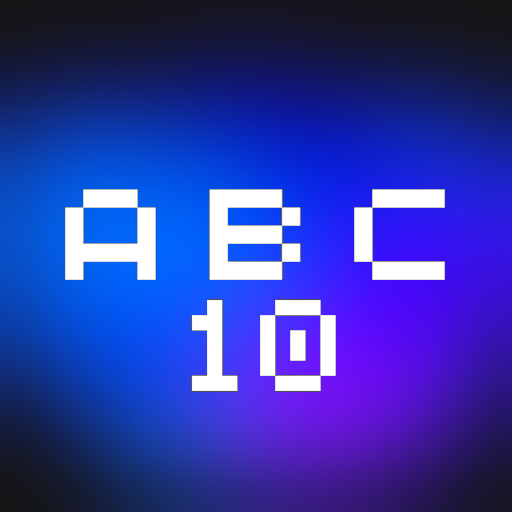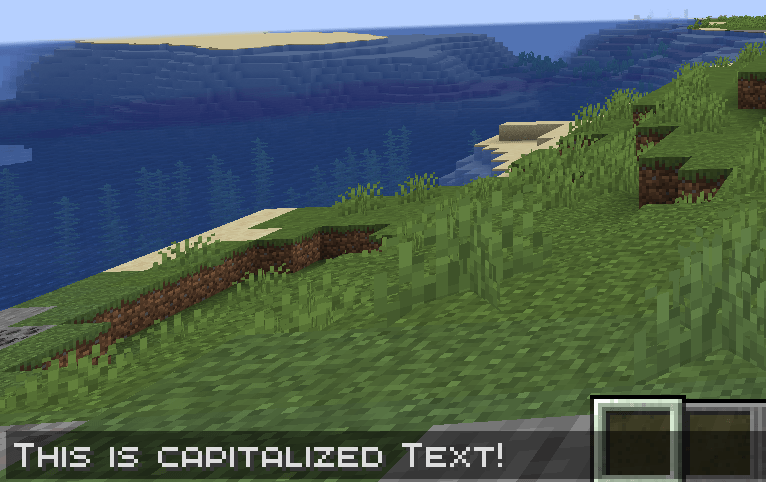
Капитализация текста в Minecraft: как получить стильный шрифт на серверах
Вы замечали на некоторых серверах Minecraft необычный шрифт, где все буквы заглавные, но выглядят аккуратно? Если вы хотели такой же для своего клиента — теперь это возможно! В этой статье разберём, как установить этот стиль, чем он отличается от стандартного и какие есть нюансы для Bedrock Edition.
🔠 Что за капитализированный шрифт?
Этот пакет ресурсов заменяет все строчные буквы на их заглавные версии, но с уменьшенным размером на 1 пиксель. Это создаёт эффект единообразия без потери читаемости. Также адаптированы цифры и спецсимволы, чтобы они гармонично сочетались с текстом.
Особенности:
- Все буквы в верхнем регистре.
- Оптимизированная высота символов.
- Поддержка кириллицы (если включено в пакете).
- Совместимость с большинством версий игры.
🔍 Где использовать такой шрифт?
Капитализированный текст отлично подходит для:
- Серверных интерфейсов — делает чат и меню более читаемыми.
- Карт для прохождения — выделяет важные подсказки.
- Видеороликов и скриншотов — добавляет стиль в оформление.
🏁 Заключение
Капитализированный шрифт — это простой способ освежить интерфейс Minecraft без сложных модификаций. Он подходит как для серверов, так и для одиночной игры, а установка занимает всего пару минут. Если вы любите экспериментировать с визуалом, попробуйте и другие ресурспаки — вариантов оформления текста в Minecraft огромное множество!